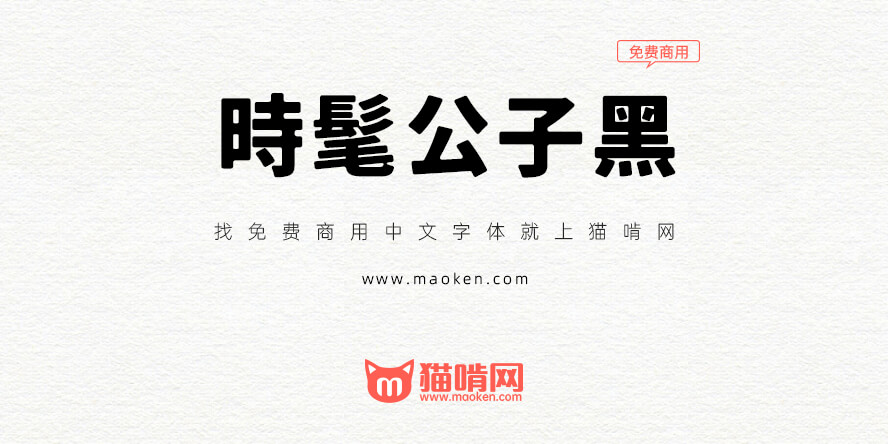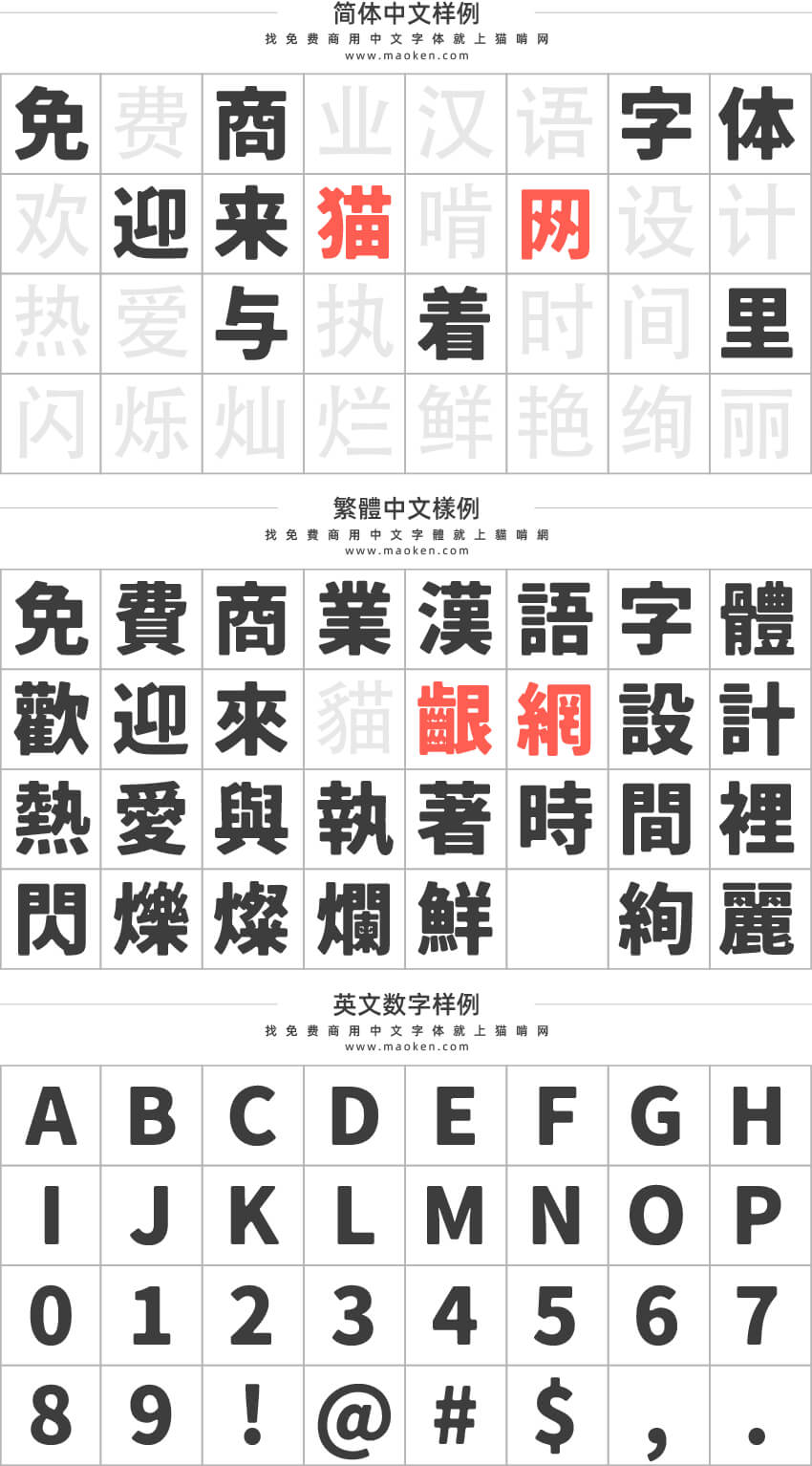
时髦公子黑:在边角上添加圆角,具有柔和复古的感觉
字体作者:FLOP DESIGN (日本) 字体字重:4个
时髦公子黑是一种具有柔和复古感的字体,通过在带有现代骨架的哥特式边角上添加圆角。 超过 8000 个字符,您可以放心使用。
我们收到了与流行的 Moga 字体 (https://flopdesign.booth.pm/items/1817411) 匹配的免费汉字字体的请求,因此我们创建了它。